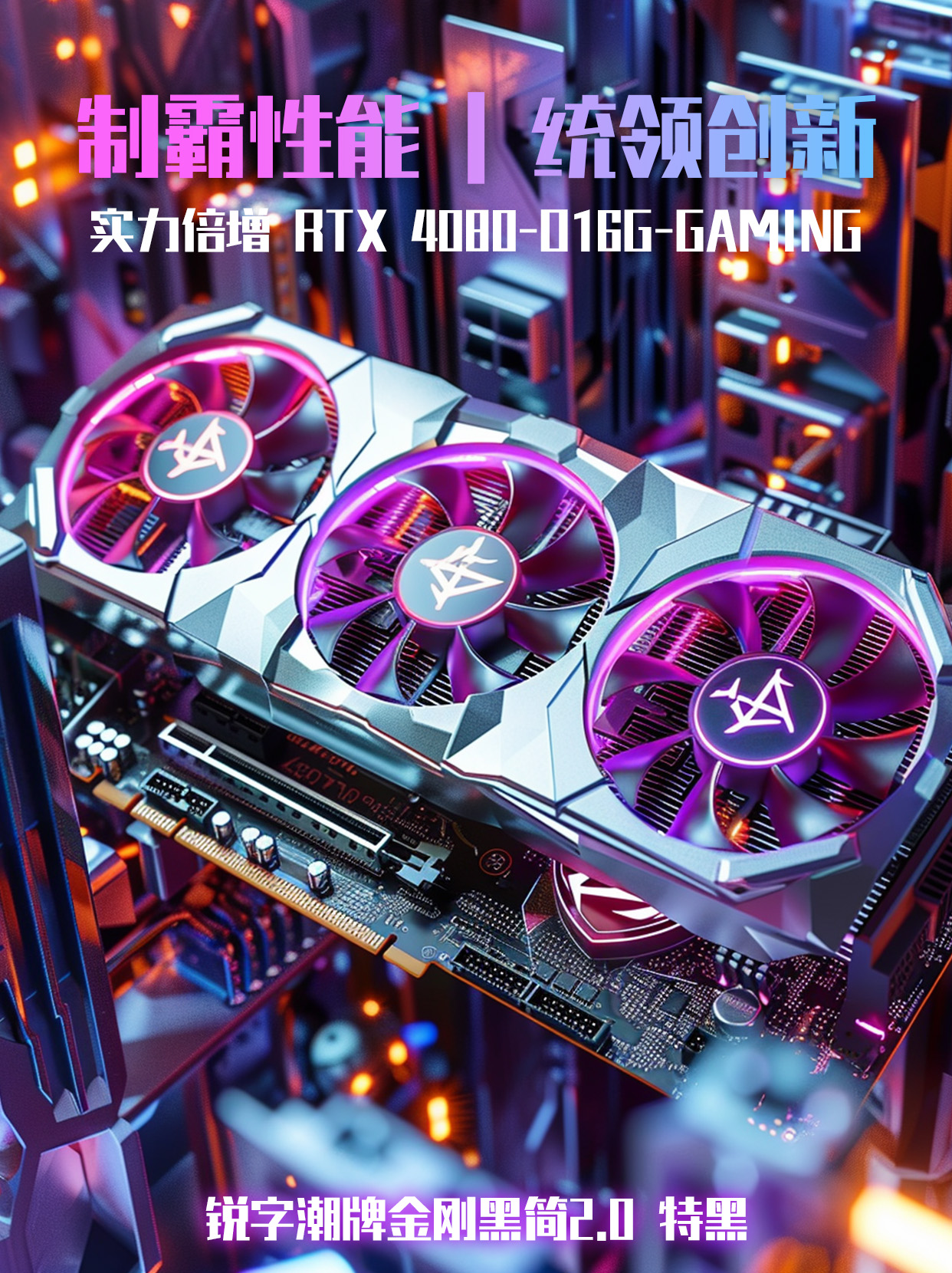
锐字潮牌金刚黑简2.0 特黑
REEJI-JinGangGB2.0 Black
原锐字工房金刚黑简1.0 粗黑现已更新升级为锐字潮牌金刚黑简2.0 特黑
简体
黑体
特黑(Black)
锐字潮牌金刚黑简是一款粗犷黑色风格的标题字,通过简单大气笔画,给人非常沉稳醒目的感觉,适合报刊、广告等标题设计。